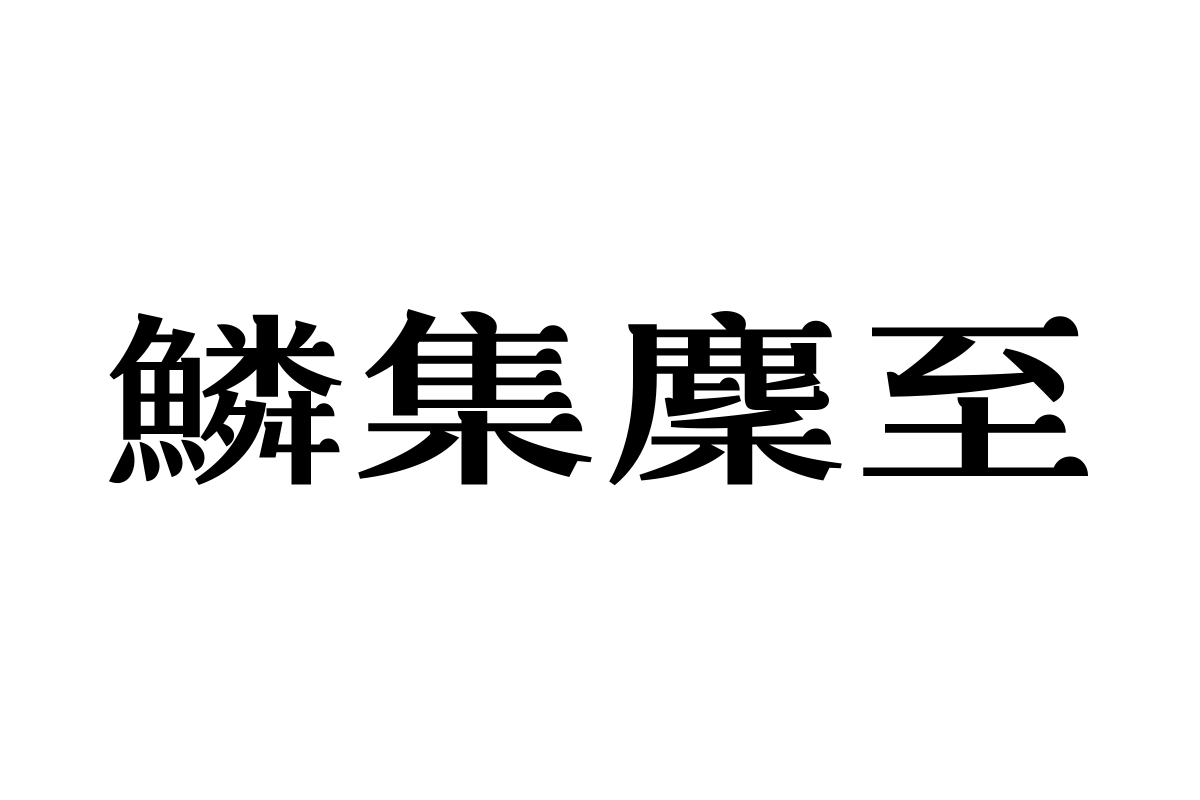
汉仪盈宋55繁体是一款具有独特风格的字体,其特点主要体现在以下几个方面:
1. 字形圆润饱满,线条流畅自然。这种字体给人一种柔和、亲切的感觉,适合用于需要传达温暖、友好氛围的场合。
2. 结构紧凑,笔画清晰。每个字的笔画都经过精心设计,使得整个字体看起来既美观又易读。
3. 风格独特,个性鲜明。汉仪盈宋55繁体采用了独特的设计手法,使其在众多字体中脱颖而出,具有较高的辨识度。
4. 适用范围广泛。无论是用于书籍、杂志、海报等印刷品的设计,还是用于网页、广告等电子媒体的制作,汉仪盈宋55繁体都能展现出其独特的魅力。
总之,汉仪盈宋55繁体是一款非常优秀的字体,无论是从审美角度还是实用角度来看,都是值得推荐的好字体。